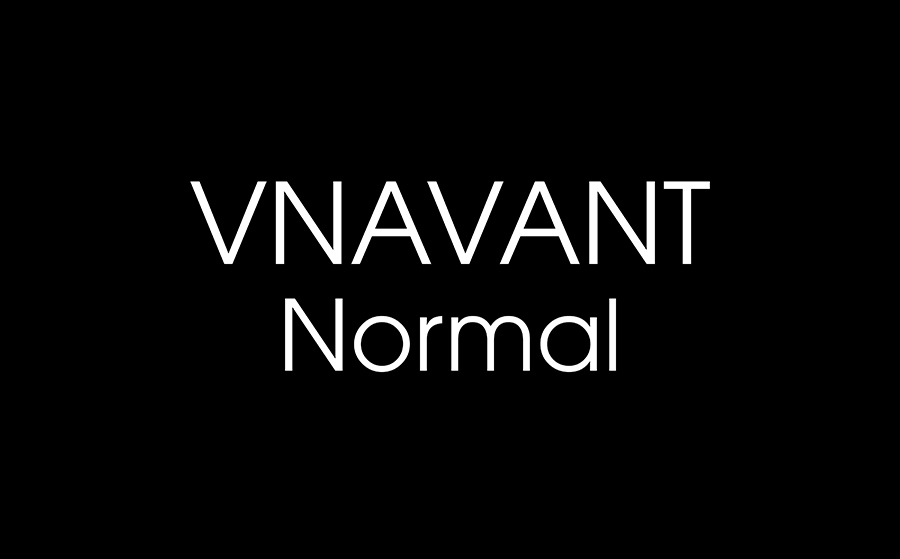
Font VnAvant là gì? Vì sao được dùng phổ biến trong giáo dục và in ấn
VnAvant thuộc bộ font TCVN3 — chuẩn mã hóa tiếng Việt được Bộ Khoa học và Công nghệ ban hành, từng là tiêu chuẩn quốc gia trước khi Unicode phổ biến rộng rãi. Font được thiết kế theo kiểu chữ Avant Garde — dáng tròn, đều, không chân — mang lại cảm giác thân thiện, dễ đọc, phù hợp với đối tượng trẻ em và tài liệu giảng dạy.
Ba lý do khiến VnAvant vẫn được dùng phổ biến đến nay:
- Gắn liền với sách giáo khoa và tài liệu giáo dục: nhiều bộ tài liệu mầm non, tiểu học được soạn từ thời kỳ TCVN3 vẫn dùng VnAvant làm font chính. Khi chỉnh sửa hoặc bổ sung tài liệu cũ, cần đúng font để không bị vỡ bố cục.
- Dáng chữ tròn, dễ đọc cho trẻ nhỏ: các giáo viên mầm non và tiểu học ưa dùng VnAvant cho flashcard, bảng chữ cái, phiếu bài tập vì nét chữ rõ ràng, không gây nhầm lẫn cho trẻ mới học đọc.
- Phổ biến trong in ấn địa phương: nhiều xưởng in và cơ sở thiết kế lâu năm vẫn lưu file dưới định dạng TCVN3, cần đúng bộ font VnAvant để mở và chỉnh sửa không bị lỗi.
Tổng quan 4 kiểu chữ trong bộ VnAvant
Bộ VnAvant đầy đủ gồm 4 kiểu chữ, mỗi kiểu phục vụ một mục đích khác nhau trong thiết kế tài liệu và ấn phẩm in.
| Kiểu chữ | Tên file | Đặc điểm | Dùng cho |
|---|---|---|---|
| Normal | VnAvant | Đứng, nét thường | Nội dung chính, văn bản hành chính giáo dục, phiếu bài tập |
| Italic | VnAvant-Italic | Nghiêng | Nhấn mạnh thuật ngữ, chú thích, trích dẫn trong tài liệu giảng dạy |
| Bold | VnAvant-Bold | Đậm | Tiêu đề, đầu mục, từ khóa cần nổi bật trong phiếu học tập |
| Bold Italic | VnAvant-BoldItalic | Đậm và nghiêng | Tiêu đề phụ, nhấn mạnh đặc biệt trong tài liệu nhiều cấp độ thông tin |
VnAvant và VnAvantH khác nhau ở điểm nào?
Đây là câu hỏi thường gặp nhất khi dùng bộ font TCVN3. Hai tên trông gần giống nhau nhưng phục vụ hai bảng mã hoàn toàn khác nhau.
- VnAvant dùng bảng mã TCVN3 (ABC) – bảng mã tiếng Việt cũ, phổ biến trong các file Word, CorelDRAW và tài liệu được tạo trước năm 2005. Khi mở file cũ mà thấy chữ bị lỗi hiển thị thành ký tự lạ, đó là dấu hiệu file đang dùng bảng mã TCVN3 và cần cài đúng bộ VnAvant.
- VnAvantH dùng bảng mã VNI – một chuẩn mã hóa tiếng Việt khác, song song tồn tại với TCVN3 trong cùng thời kỳ. File tạo bằng phần mềm hỗ trợ VNI sẽ cần VnAvantH để hiển thị đúng.
Cách nhận biết nhanh: nếu gõ tiếng Việt ra chữ đúng với bộ font này thì đó là bảng mã phù hợp. Nếu chữ vẫn hiện ký tự lạ sau khi cài VnAvant, thử cài thêm VnAvantH và chuyển bảng mã gõ sang VNI để kiểm tra.
Font VnAvant mầm non khác VnAvant thông thường ở điểm nào?
VnAvant mầm non thường chỉ là tên gọi thông dụng của font VnAvant Normal dùng trong tài liệu giáo dục cho trẻ nhỏ, không phải một phiên bản riêng biệt. Bộ font tải về đã bao gồm kiểu chữ này.
VnAvant có hỗ trợ Unicode không?